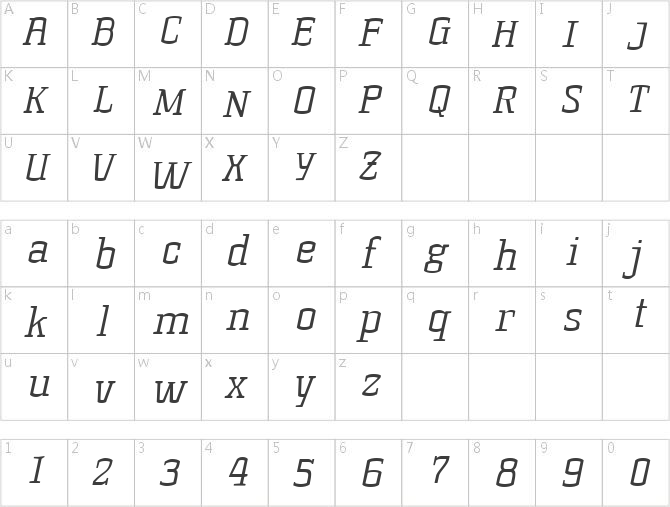
KorneuburgSlabLight-LightItalic
KorneuburgSlabLight-LightItalic介紹
KorneuburgSlabLight-LightItalic字體字庫是一款讓人賞心悅目、百看不厭的英文字體,適合各類廣告和產品包裝設計應用,字體大小0.04MB,格式為ttf字體,上傳用戶是Me / ,yD ,作者/版權方為未知